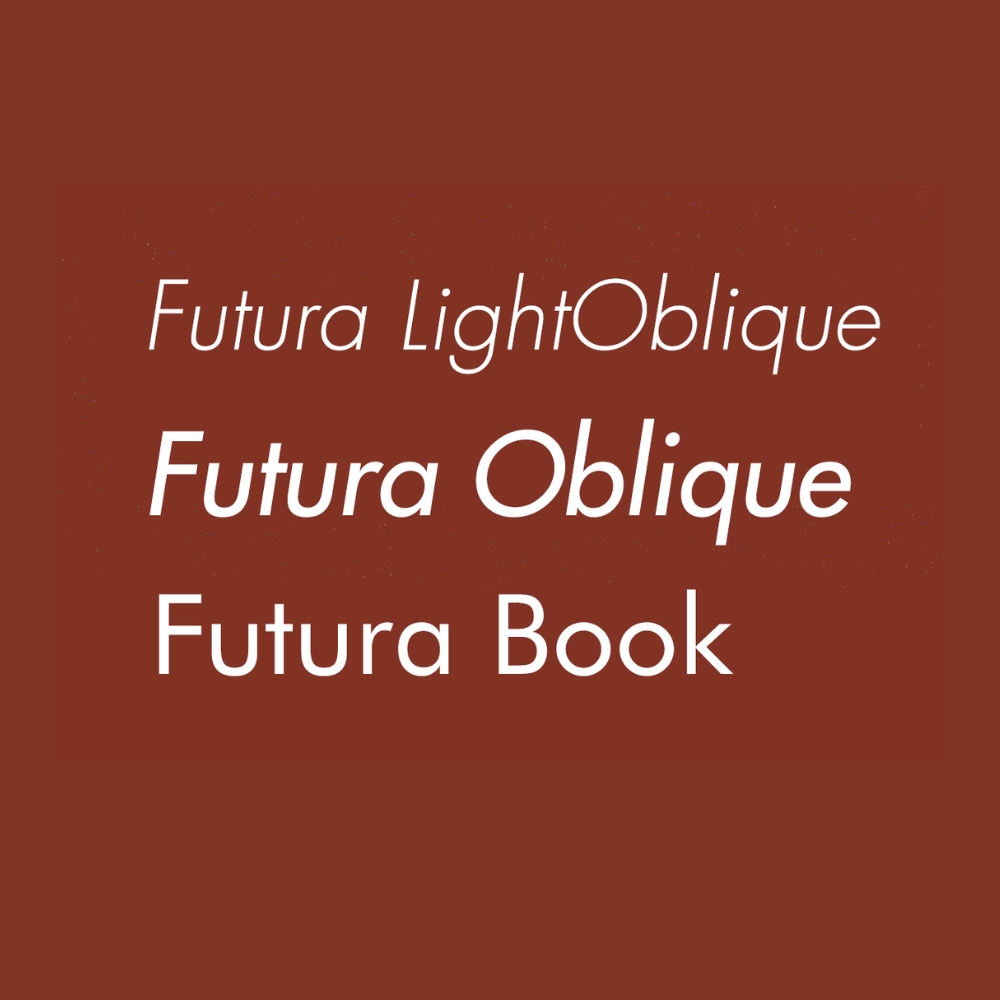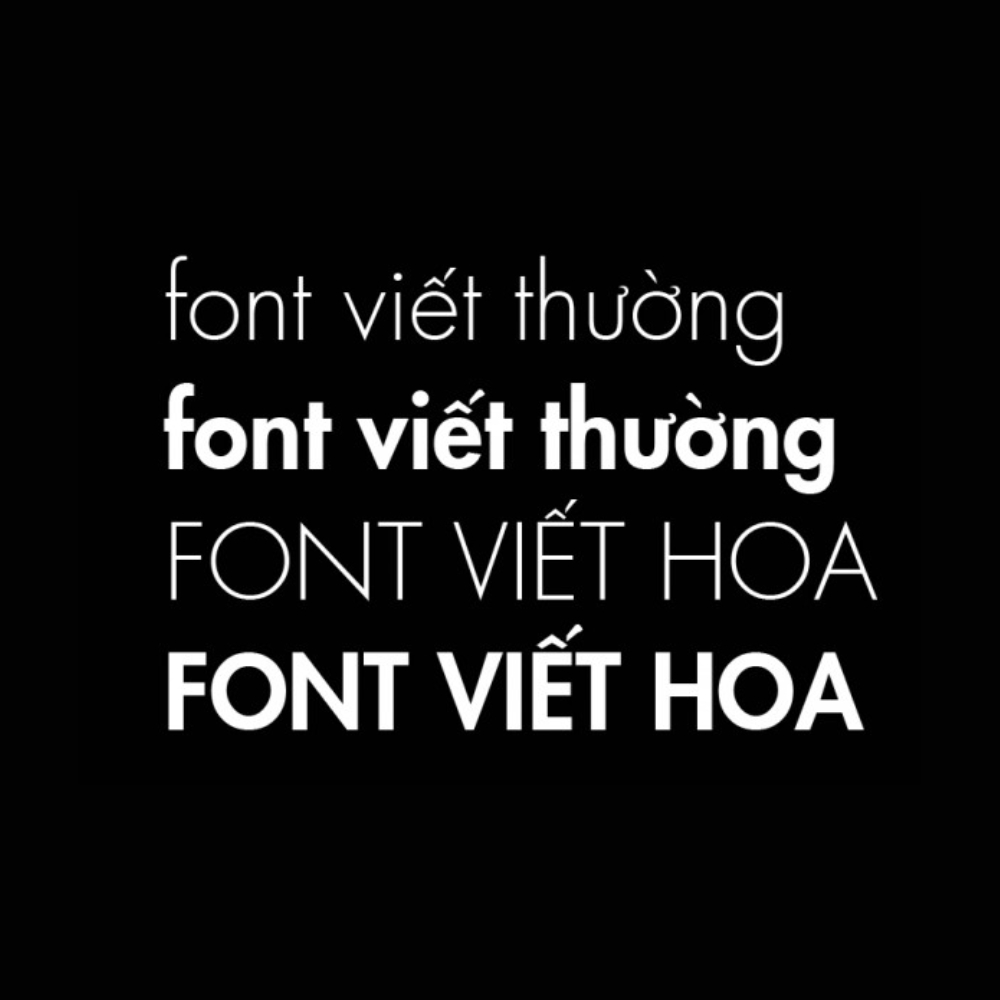
Font Futura là font chữ hình học kinh điển của thiết kế hiện đại với phong cách sạch sẽ, tối giản được sử dụng rộng rãi trong thiết kế bao bì cao cấp, túi giấy thương hiệu thời trang và in logo cho các dự án kiến trúc. Font Futura việt hóa với nét chữ hoàn hảo về mặt hình học tạo cảm giác tiến bộ, thanh lịch.
Phông chữ Futura là gì?
Font Futura được thiết kế năm 1927 bởi Paul Renner – nhà thiết kế chữ người Đức. Tên “Futura” nghĩa là “tương lai” – phản ánh tầm nhìn của Renner về font chữ cho thời đại mới, tiến bộ.
Futura là đại diện tiêu biểu của phong trào hiện đại chủ nghĩa Đức. Renner bị ảnh hưởng bởi trường Bauhaus, tin rằng thiết kế tốt nhất dựa trên hình học thuần túy, loại bỏ mọi chi tiết không cần thiết.
Futura được xây dựng từ hình tròn hoàn hảo, hình tam giác và hình vuông không một nét cong tự nhiên. Đặc điểm của phông chữ Futura:
- Hình học hoàn hảo: Chữ O là hình tròn chuẩn, không oval. Chữ M có góc nhọn như tam giác. Mọi thứ tuân theo quy tắc hình học.
- Tối giản: Không chân, không trang trí – chỉ giữ hình dạng cơ bản nhất.
- Thanh lịch: Mặc dù hình học cứng nhắc nhưng Futura vẫn thanh lịch, không lạnh lùng như font hình học khác.
- Đa năng: Có nhiều độ đậm từ Light đến Bold, phù hợp cả tiêu đề và nội dung.
| Tên font | Đặc điểm |
Ứng dụng in ấn |
Futura (gốc) |
Font thương mại, nhiều độ đậm. | Logo cao cấp, bao bì thời trang xa xỉ. |
Spartan |
Font miễn phí rất giống Futura. | Thay thế tốt nhất cho Futura. |
Montserrat |
Font hình học đa năng, 18 độ đậm. | Logo, bao bì giấy, túi giấy linh hoạt. |
Josefin Sans |
Font hình học thanh lịch, vintage. | Bao bì thời trang, túi giấy spa, lifestyle. |
Raleway |
Font hình học tinh tế, 18 độ đậm. | Logo tối giản, túi giấy cao cấp. |
Questrial |
Font hình học đơn giản, sạch sẽ. | Bao bì hiện đại, nhãn sản phẩm. |
Ứng dụng phông chữ Futura trong bao bì và túi giấy
Futura font việt hóa với phong cách hình học thanh lịch được ưa chuộng:
- Biểu tượng xa xỉ: Louis Vuitton, Dolce & Gabbana, Calvin Klein đều dùng Futura – tạo liên hệ với thời trang cao cấp khi in trên bao bì, túi giấy.
- Hiện đại vượt thời gian: Thiết kế gần 100 năm trước nhưng vẫn trông tiên tiến – bao bì, túi giấy dùng Futura không bao giờ lỗi mốt.
- Thanh lịch không rườm rà: Hình học thuần túy nhưng Futura vẫn thanh lịch trên bao bì – không lạnh lùng, không cứng nhắc.
- Đa năng: Dùng được cho cả logo, tiêu đề lớn, thông tin sản phẩm trên bao bì, túi giấy.
Font chữ Futura xuất hiện trong nhiều sản phẩm:
- Túi giấy thời trang: túi kraft, túi couche cho thương hiệu xa xỉ, boutique cao cấp, flagship store.
- Bao bì giấy mỹ phẩm: hộp nước hoa, hộp skincare cao cấp, hộp makeup xa xỉ.
- In logo lên túi giấy: logo hình học thanh lịch cho thương hiệu thời trang, lifestyle.
- Bao bì giấy sản phẩm thiết kế: hộp đồ nội thất, hộp đồ gia dụng cao cấp.
- Túi giấy nghệ thuật: túi giấy phòng tranh, túi giấy triển lãm, túi giấy bảo tàng.
- In logo lên bao bì: logo tối giản cho sản phẩm cao cấp, sang trọng.
3. Tại sao Futura được các thương hiệu xa xỉ yêu thích?
Futura kết hợp hình học hoàn hảo (hiện đại, tiến bộ) với sự thanh lịch (không lạnh lùng). Font vừa đơn giản vừa tinh tế – đúng triết lý “ít mà chất” của xa xỉ đương đại.